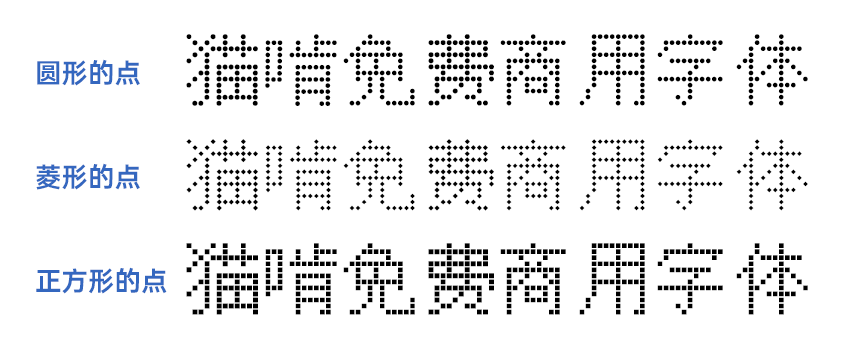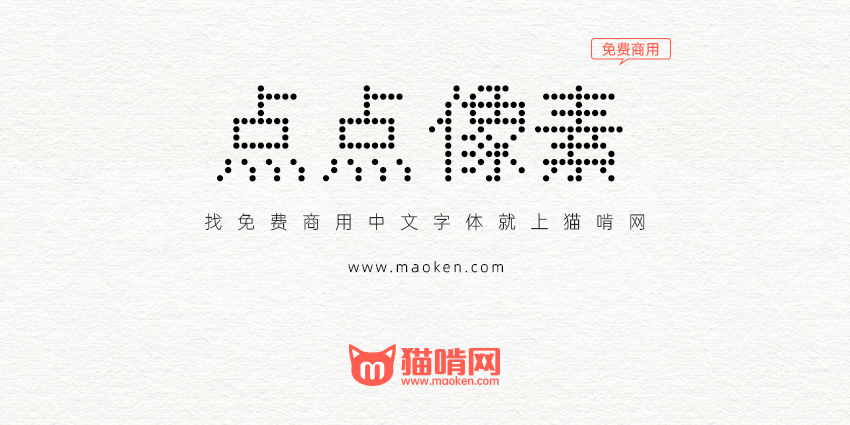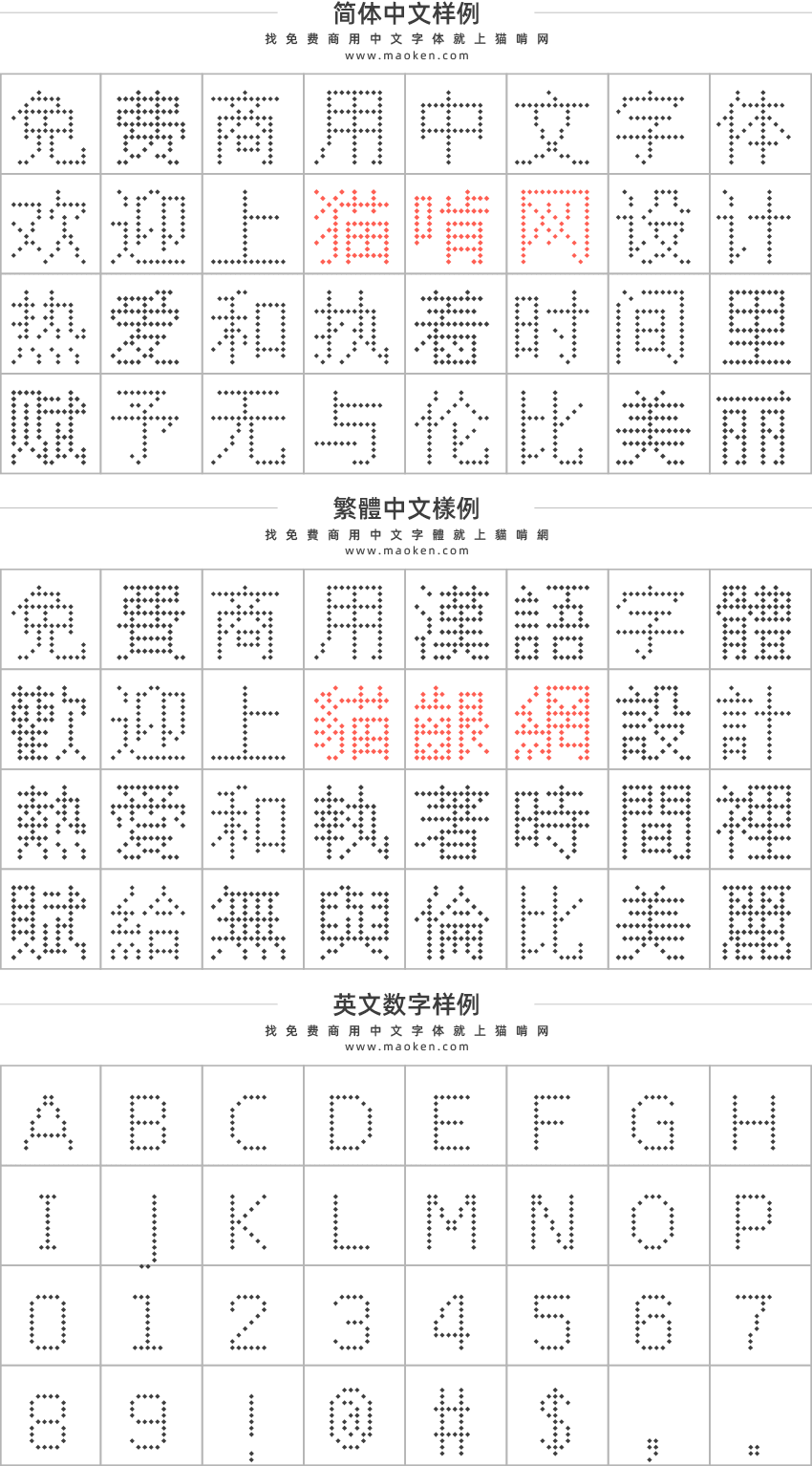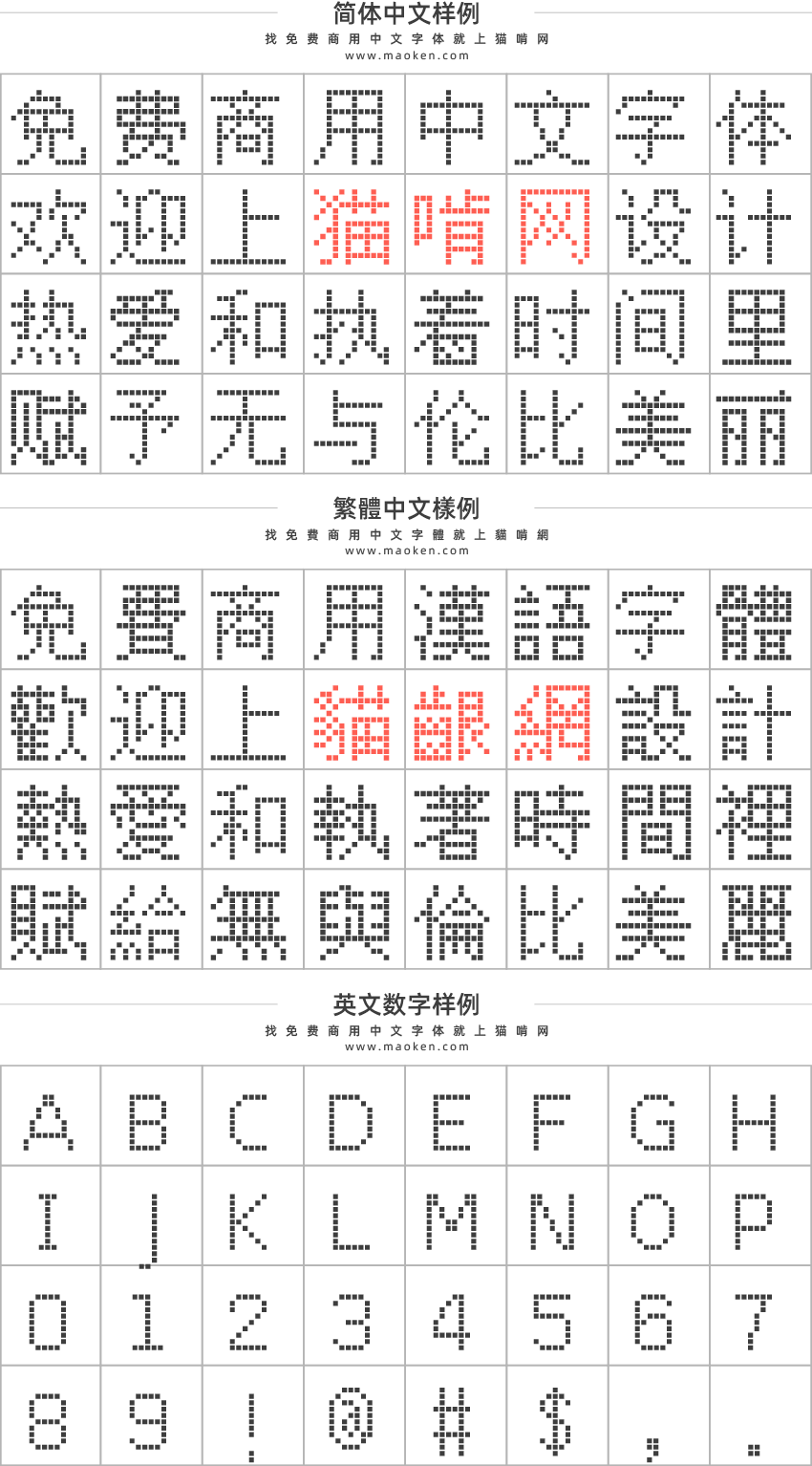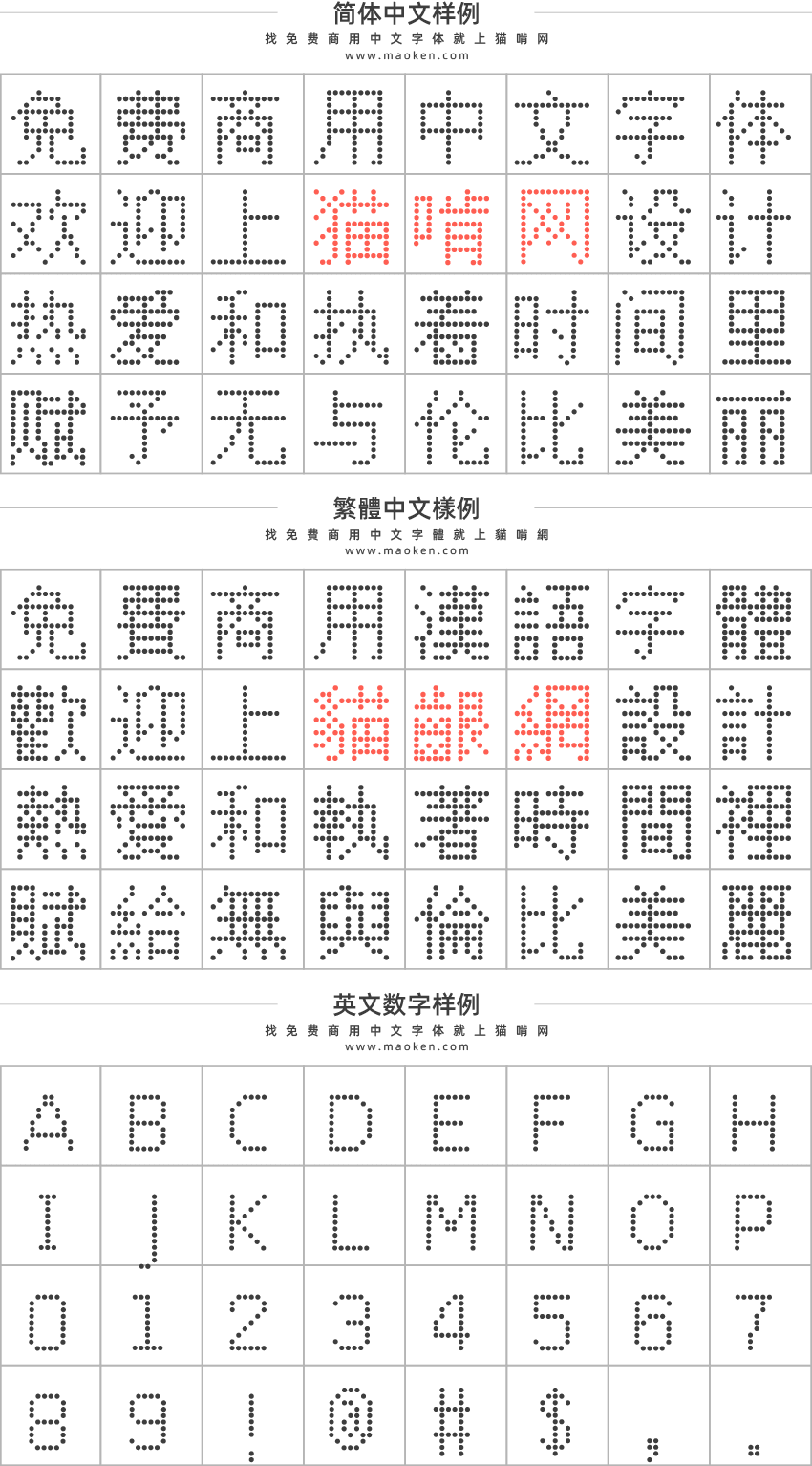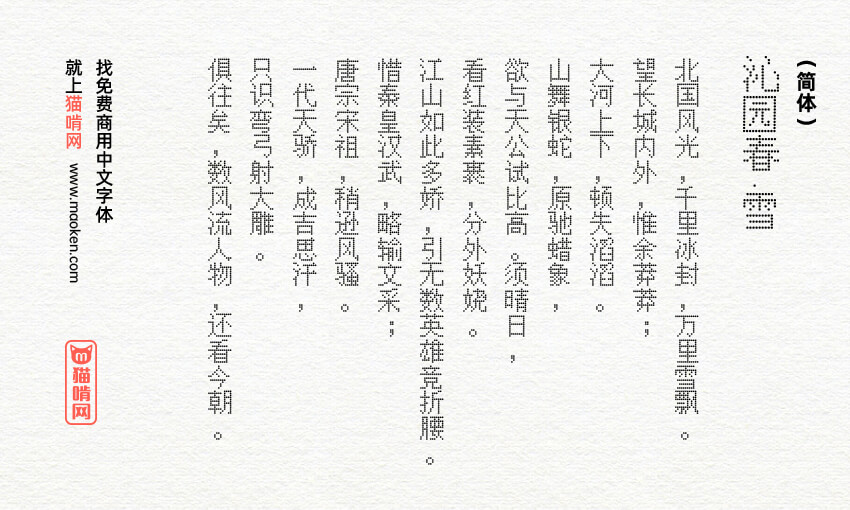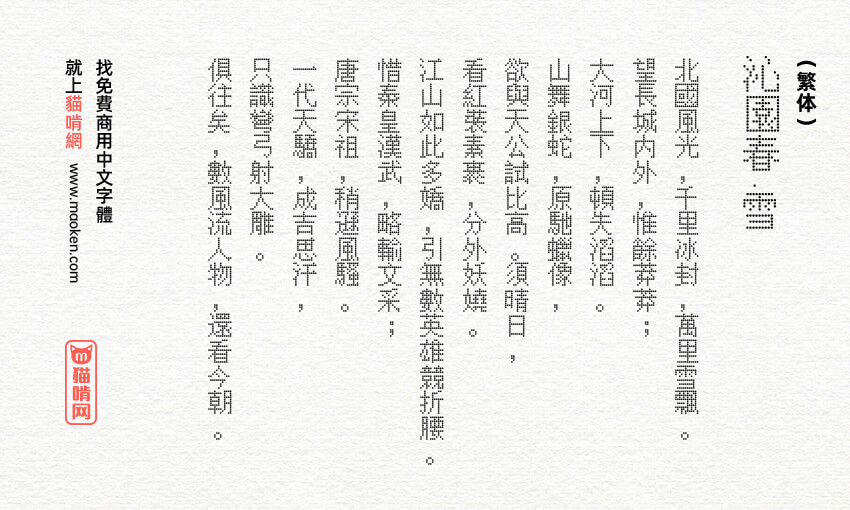
点点像素字体:开源的中文像素字体 基于文泉驿点阵宋
点点中文像素字体是一组基于GPL 2.0协议开源发布的中文像素艺术字体,每种字体均支持超过22000个Unicode字形,覆盖GBK编码中的全部简繁体汉字。
目前发布的点点像素字体都是基于文泉驿项目所创建的一 种点阵字体衍生而来的。它们是文泉驿点阵宋体经矢量化之后,通过变形、美化而得到的。文泉驿点阵宋体是基于GPL 2.0协议开源的自由字体。请访问wenq.org以获取该字体的更多信息。
参考 converter/中的源代码。该代码自动将文泉驿点阵宋体中的字型矢量化,然后变形加工为不 同风格的 OpenType 字体。在下载的字体文件包中,包括三个字体文件,主要的区别是字体的点的形状不一样。有三个样式,一个是圆形的点,一个是方形的点,还有一个是菱形的点。
目前发布的点点像素字体都是基于文泉驿项目所创建的一 种点阵字体衍生而来的。它们是文泉驿点阵宋体经矢量化之后,通过变形、美化而得到的。文泉驿点阵宋体是基于GPL 2.0协议开源的自由字体。